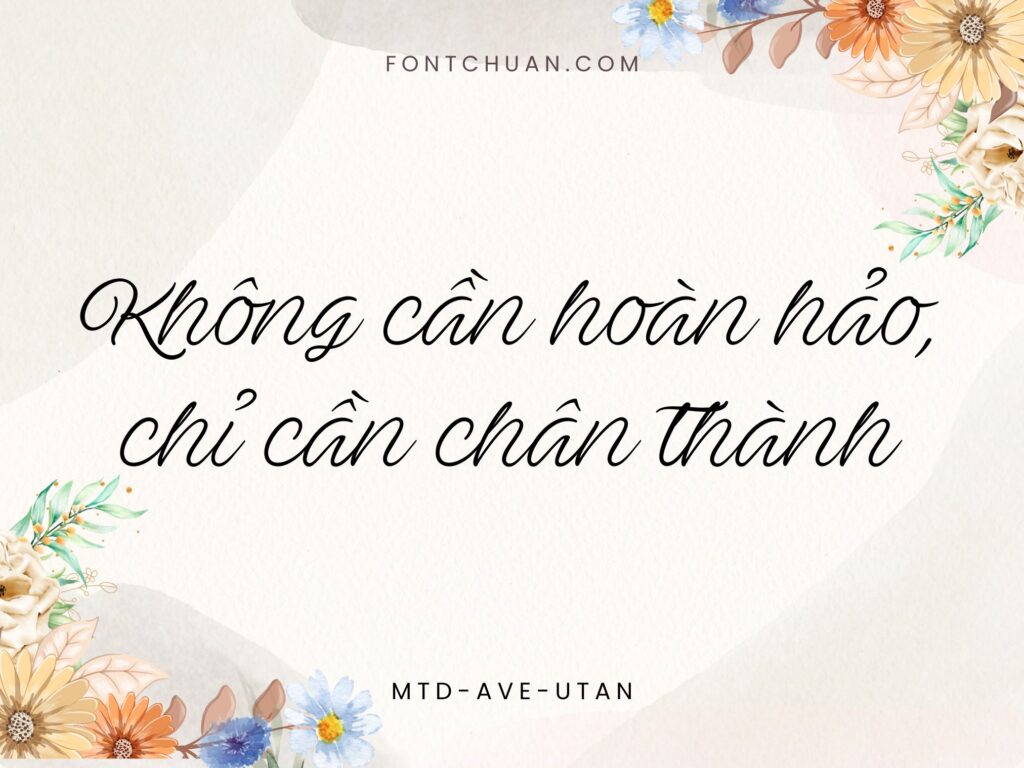
Font MTD Ave Utan Việt Hóa
Tác giả Font: Mans Greback
Ave Utan là một font chữ đầy cá tính được thiết kế bởi Mans Greback, một nhà thiết kế nổi tiếng với các font mang phong cách nghệ thuật mạnh mẽ. Font này có thiết kế đậm chất viết tay, với các đường nét bay bổng nhưng vẫn giữ được sự chắc chắn, giúp tạo điểm nhấn cho các dự án thiết kế. Để mở rộng khả năng sử dụng, Mộc Hạ đã Việt hóa font Ave Utan, giúp hỗ trợ đầy đủ tiếng Việt cùng hơn 200 ngôn ngữ khác. Phiên bản Việt hóa này đã được thành viên Font Chuẩn sưu tầm và đăng tải nhằm phục vụ cộng đồng thiết kế, mang đến sự lựa chọn sáng tạo cho các dự án nghệ thuật.
Về đặc điểm thiết kế, Ave Utan sở hữu đường nét mềm mại nhưng mạnh mẽ, phù hợp với phong cách viết tay hiện đại. Các ký tự được thiết kế với độ linh hoạt cao, kết hợp với ligatures đặc trưng giúp tăng độ tự nhiên khi sử dụng. Font này rất thích hợp cho các thiết kế logo, thương hiệu, typography sáng tạo, và đặc biệt phù hợp với ngành quảng cáo, thiết kế thiệp cưới và truyền thông. Ngoài ra, Ave Utan còn là lựa chọn lý tưởng cho các sự kiện sáng tạo như Valentine, Sinh nhật và các lễ hội, nơi cần một phong cách nổi bật và thu hút.